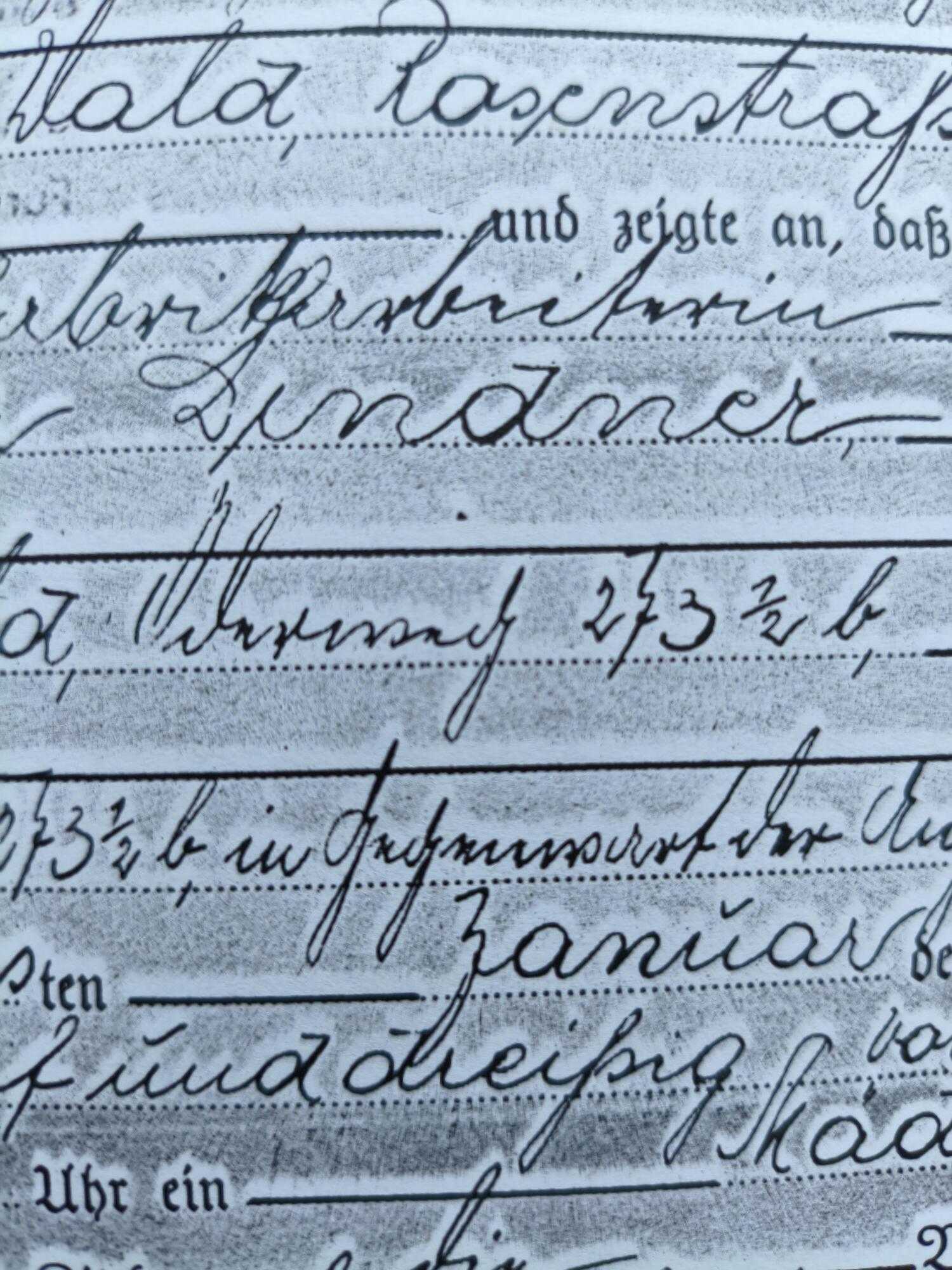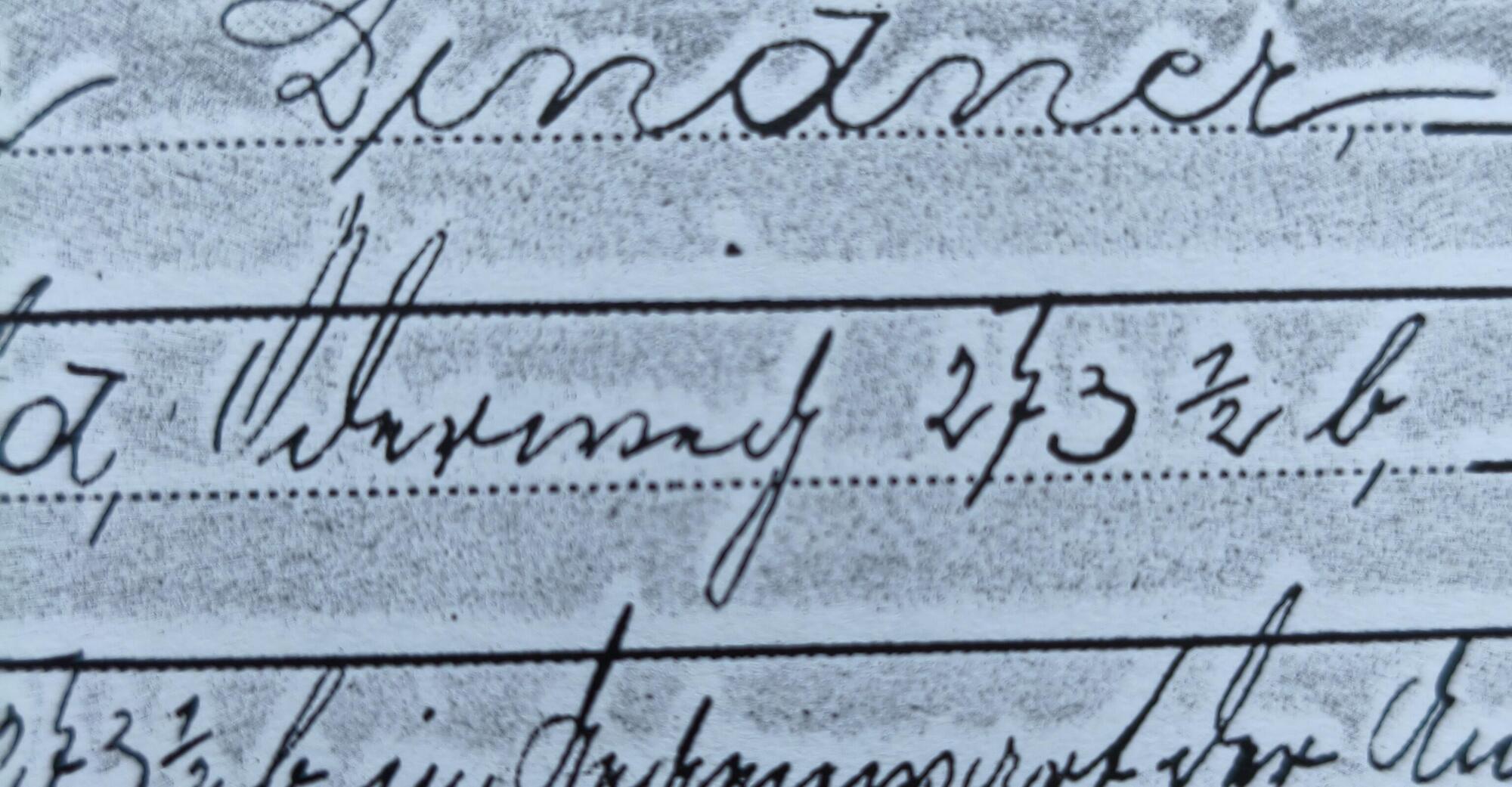
wie heißt dieses Wort? Es handelt sich um einen Ortsteil oder eine Straße in einer Geburtsanzeige von 1935
Hier ist ein größerer Ausschnitt. Ich interpretiere die letzten Buchstaben als 'ch'
Darf ich fragen, in welcher Stadt wir uns befinden? Der Kringel über dem Anfangsbuchstaben könnten ö-Striche sein. Einen Oeder Weg 273 gibt es heute z.B. in Frankfurt.